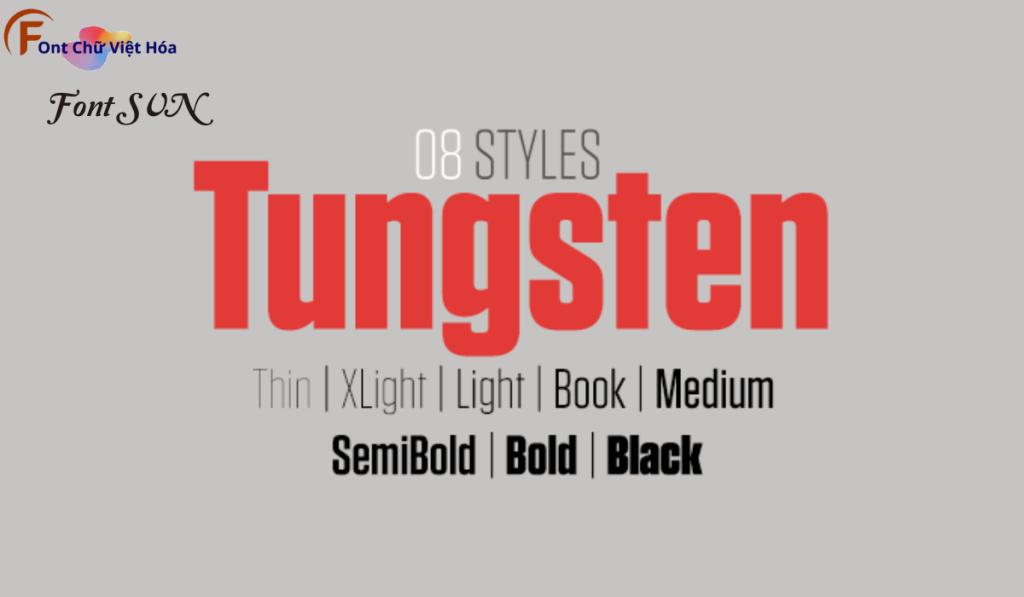
Font SVN Tungsten Việt Hóa
Ngôn ngữ: Tiếng Việt, Latin, Số
Phân loại: Cá tính, Độc đáo, Hiện đại
Độ dày: Thường, In đậm, In nghiêng, In đậm và nghiêng
Font SVN Tungsten Việt Hóa là một font chữ không chân mạnh mẽ, thuộc bộ font SVN. Được thiết kế với mục tiêu mang lại sự nổi bật và ấn tượng, font này lý tưởng cho các dự án thiết kế như tiêu đề, quảng cáo, và bao bì sản phẩm. Với các nét chữ đậm và chắc chắn, Font SVN Tungsten Việt Hóa không chỉ dễ đọc mà còn tạo cảm giác mạnh mẽ và quyết đoán. Việc Việt hóa font giúp người dùng dễ dàng sử dụng trong các thiết kế tiếng Việt, mang lại sự tiện lợi và thẩm mỹ cao.